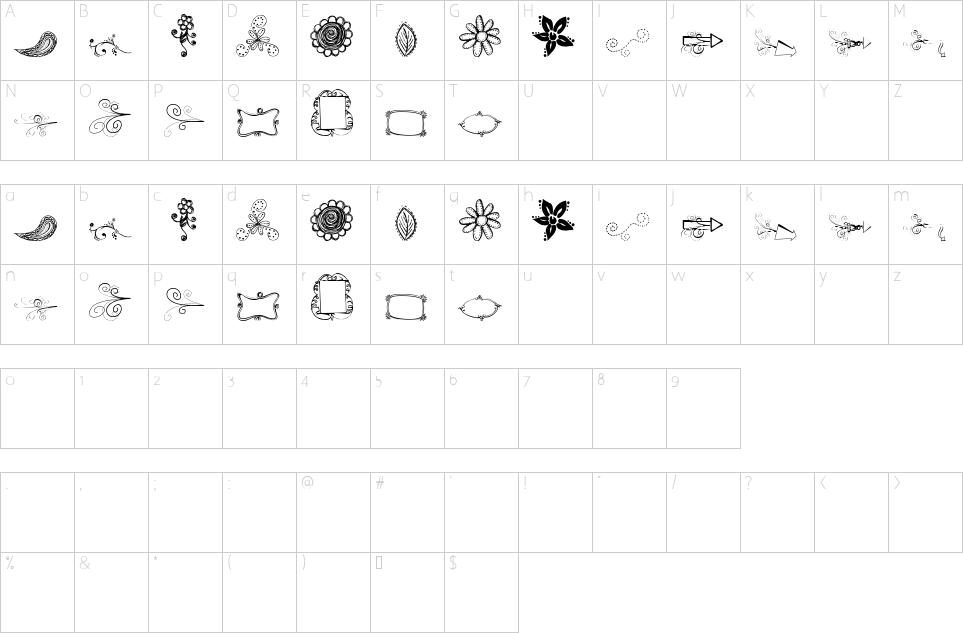
Descubra a fonte MTF Funk Fusion, uma opção única e vibrante para adicionar um toque único a seus projetos digitais. Desenhada pela talentosa designer Miss Tiina Fonts, essa fonte MTF Funk Fusion é perfeita para aqueles que buscam uma fonte com um estilo único e vibrante. Foi criada especialmente para criar um efeito de música funk e fusão, tornando-a perfeita para designers de sites, gráficos e aplicativos. Com um design simples e elegante que também consegue capturar a energia dinâmica da música, esta fonte está disponível para download para Windows e Mac, já que foi projetada para atender a uma ampla gama de necessidades de design. Com MTF Funk Fusion, você não precisará buscar outra fonte para dar vida e movimento ao seu próximo projeto. Você pode ter acesso a esta fonte de graça, sem comprometer a qualidade ou personalização de sua obra. Sinta-se à vontade para experimentar, pois o impacto de uma boa fonte pode fazer toda a diferença em seus projetos.